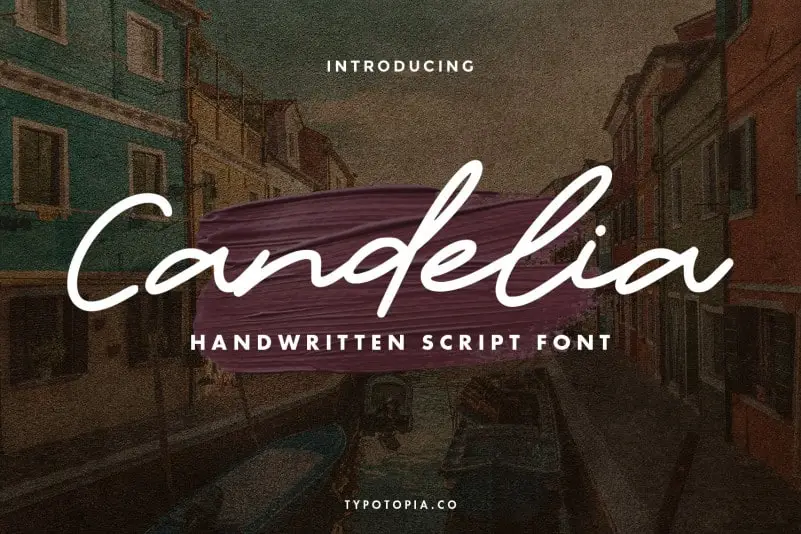
Candelia Handwritten Font – Download Grátis
A Candelia Handwritten Font é uma delicada escolha para designers que buscam um tom aconchegante e natural no seu trabalho. Esta elegante tipografia foi criada especificamente para aplicações em diversos formatos, como logotipos, moda, embalagens, cartões de convite, livros, revistas e mais. Seu charme desenhado à mão permite que a Candelia seja usada de maneiras versáteis, tornando-a perfeita para estilos variados. Seja para dar um toque sofisticado em sua marca ou para adicionar uma personalidade única aos seus projetos, essa fonte é uma ótima opção. Não apenas ela oferece beleza e simplicidade, mas também flexibilidade de uso que fará seu trabalho mais envolvente. E com o designer tipotopia por trás dela, pode-se esperar não só estética agradável como também um design cuidadosamente elaborado para diferentes contextos de aplicação. Com Candelia Handwritten Font, você tem à mão uma ferramenta versátil e sofisticada que pode complementar suas criações de forma única.